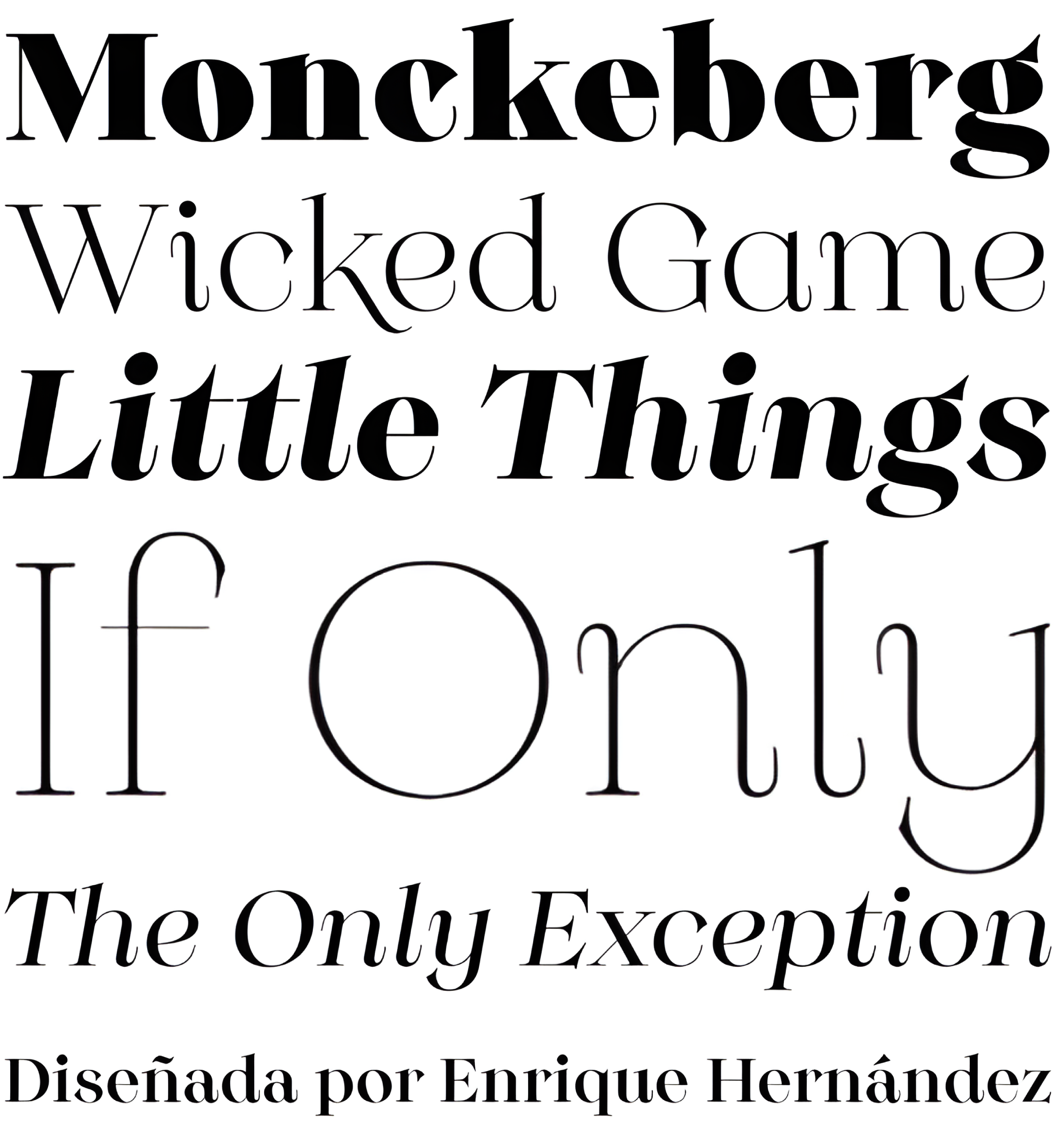
| Año | 2019 |
| Créditos | Enrique Hernández |
| Descripción | Monckeberg es una fuente expresiva con una fuerte personalidad que se basa en los tipos de letra venecianos clásicos del siglo XV. El alto contraste entre trazos finos y gruesos, los rasgos caligráficos y el acento diagonal son sus características más llamativas. Monckeberg es ideal para textos y párrafos cortos, y está especialmente diseñada para logotipos, marcas, diseño editorial y uso web. Monckeberg consta de 2 subfamilias de 9 pesos, de Thin a Heavy, con cursivas a juego, lo que da un total de 36 fuentes. La familia básica es clásica y elegante, mientras que la versión alternativa permite una mayor libertad de diseño. Monckeberg contiene 511 caracteres compatibles con más de 200 lenguas de base latina. |
| Clasificación | Texto |
| Familia(s) | Thin, Thin Italic, Extra Light, Extra Light Italic, Light, Light Italic, Normal, Normal Italic, Regular, Regular Italic, Medium, Medium Italic, Bold, Bold Italic, Black, Black Italic, Heavy, Heavy Italic, Alt Thin, Alt Thin Italic, Alt Extra Light, Alt Extra Light Italic, Alt Light, Alt Light Italic, Alt Normal, Alt Normal Italic, Alt Regular, Alt Regular Italic, Alt Medium, Alt Medium Italic, Alt |
| Estilos | 36 |